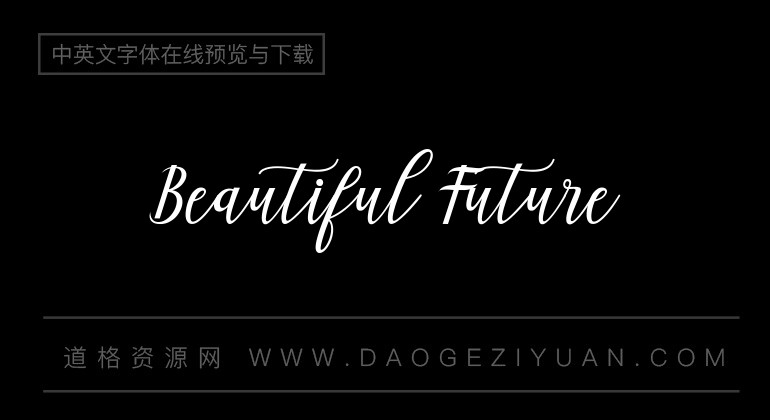
Beautiful Future
很抱歉,作为一个 AI 语言模型,我没有视觉界面,无法展示字体。但我可以告诉你 Beautiful Future 字体是由 JumboDesign 设计的一种现代化、流畅的字体。它的特点是字母的线条柔和流畅,整体看起来很舒适、优美,适用于各种设计、印刷、广告等场合。它的字体家族包含 Regular、Italic、Bold 和 Bold Italic 四种字重,可以在设计中灵活运用。
Beautiful Future是一款非常不错的手写艺术字体,具有很好的视觉感,适合于文化类的宣传设计、商业类品牌的广告和产品包装设计以及个性化文字排版等较多场景。